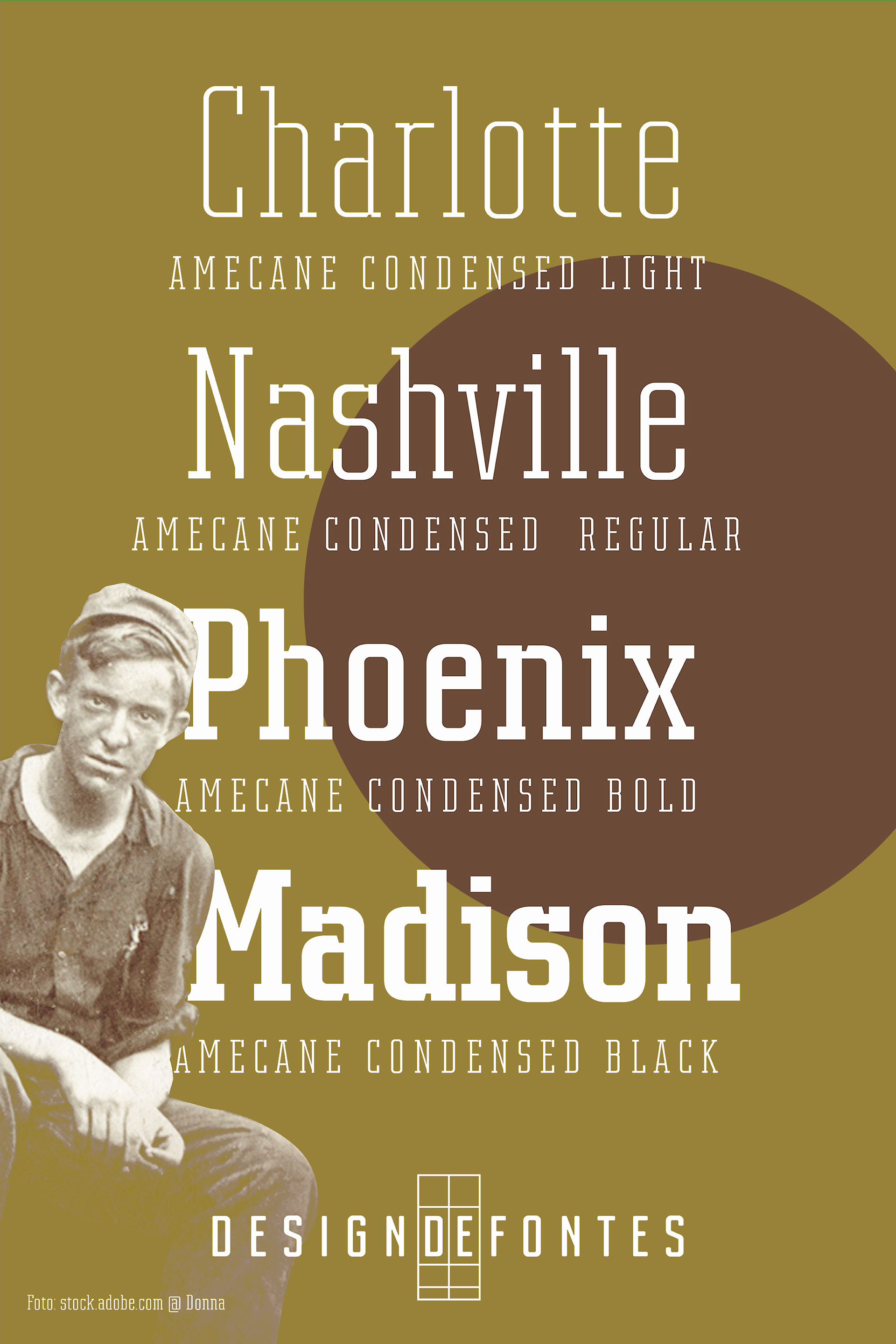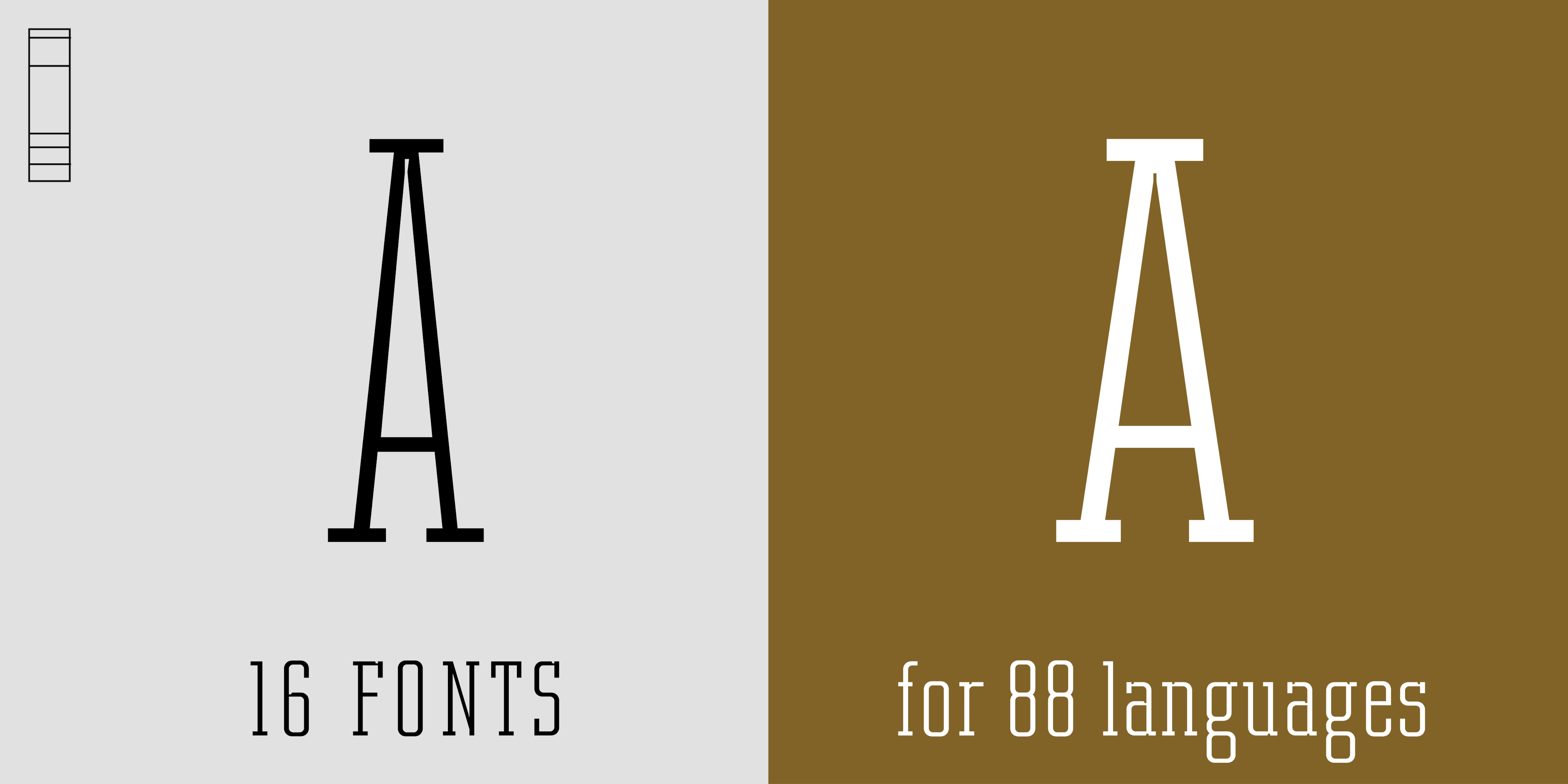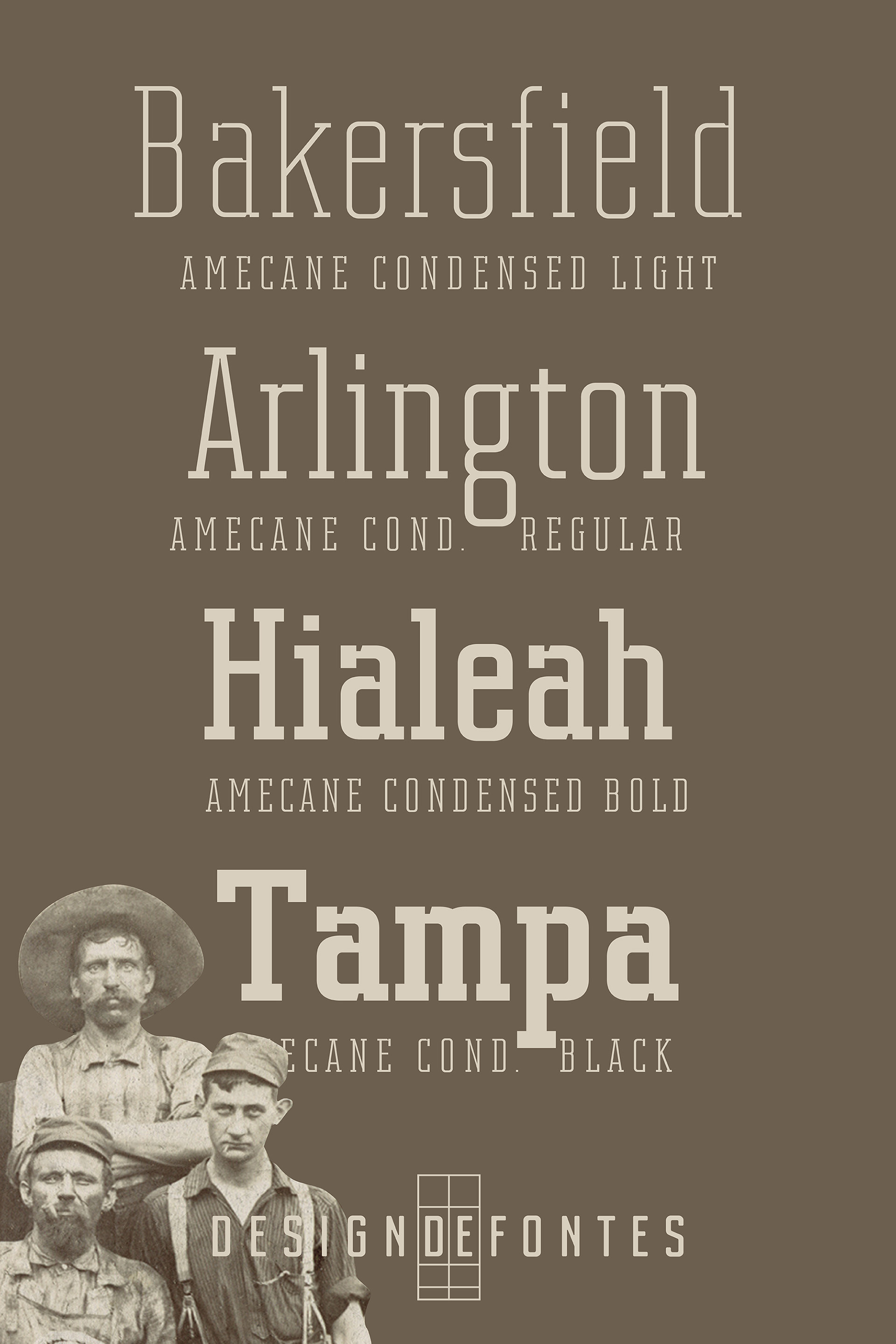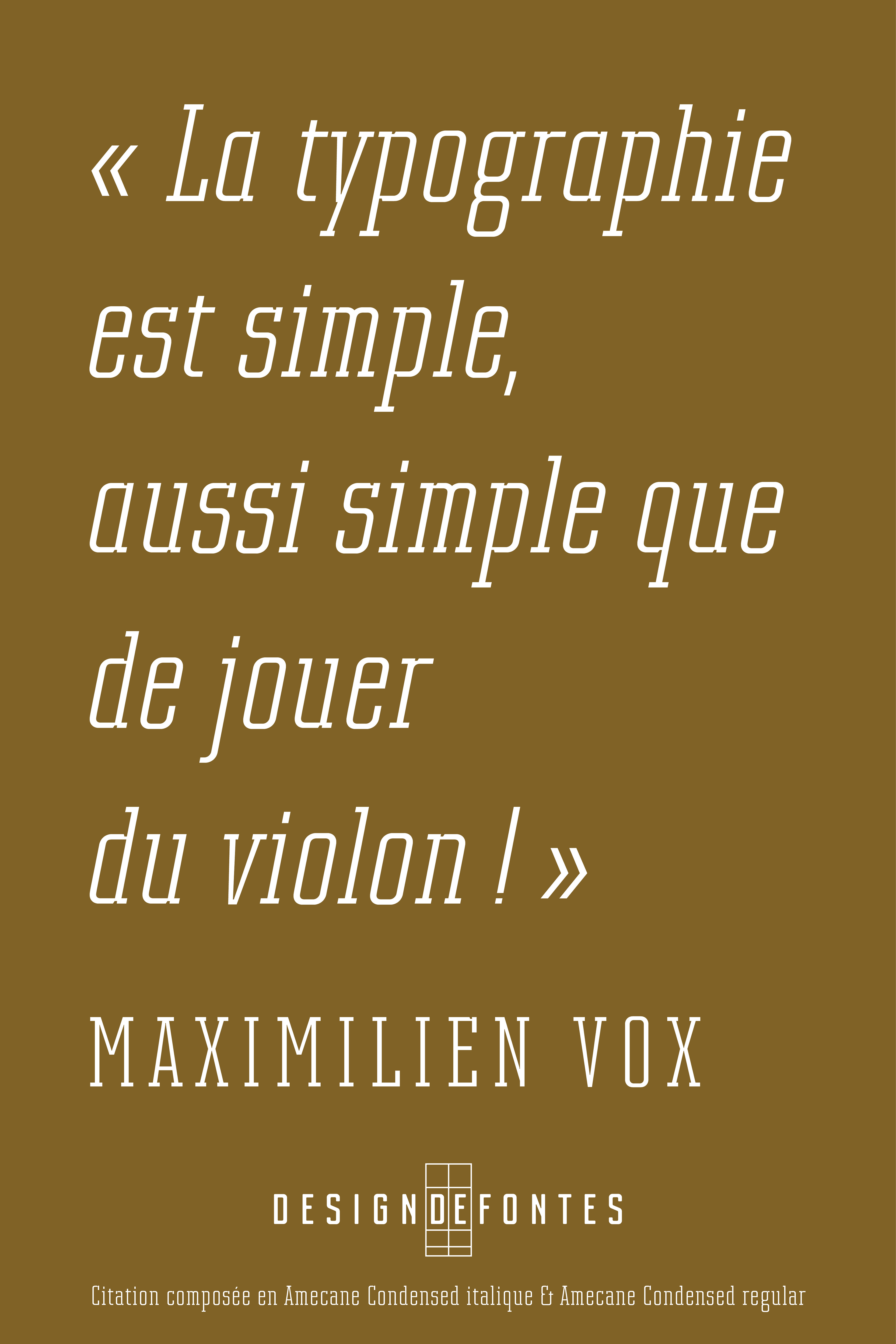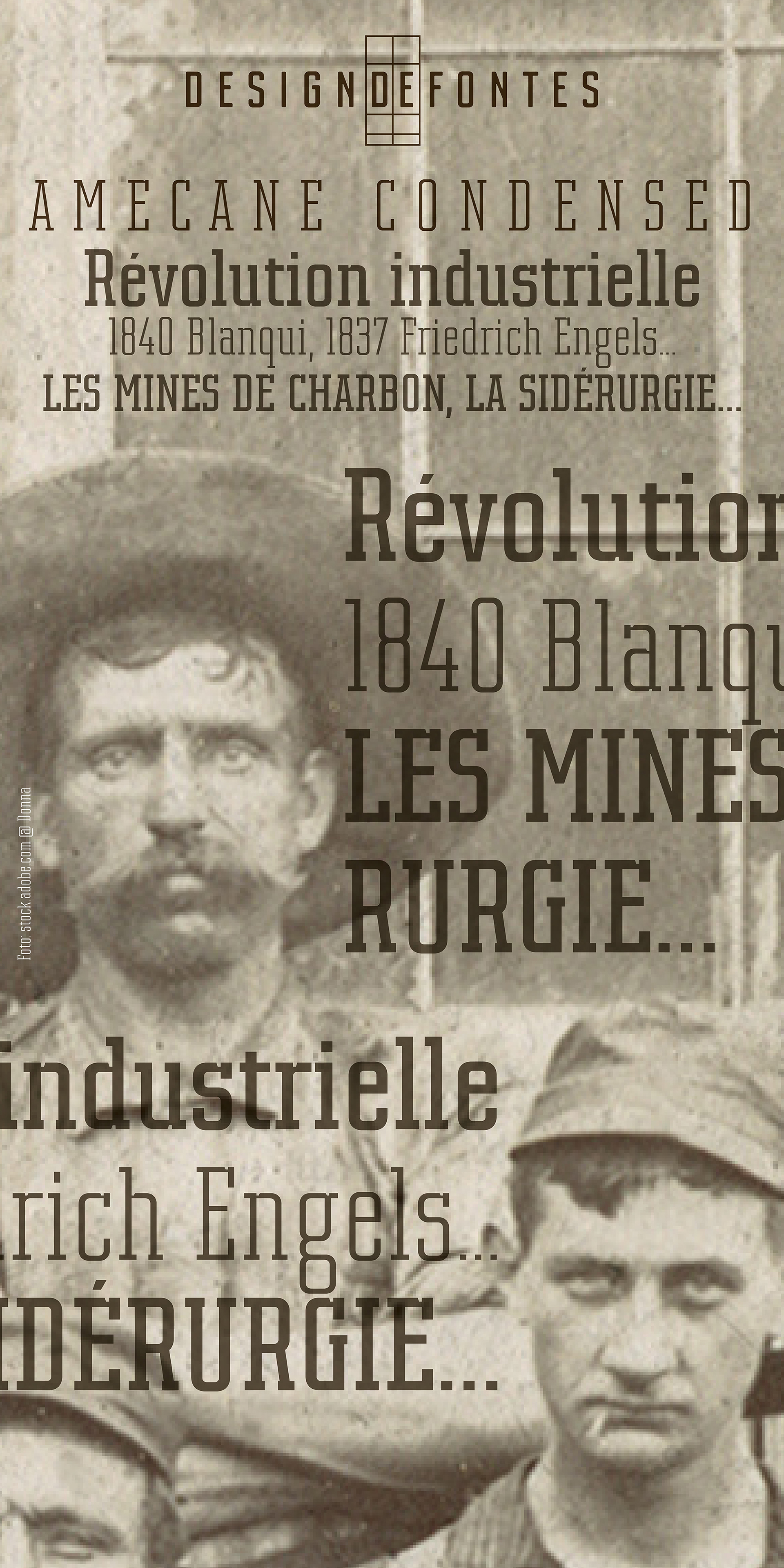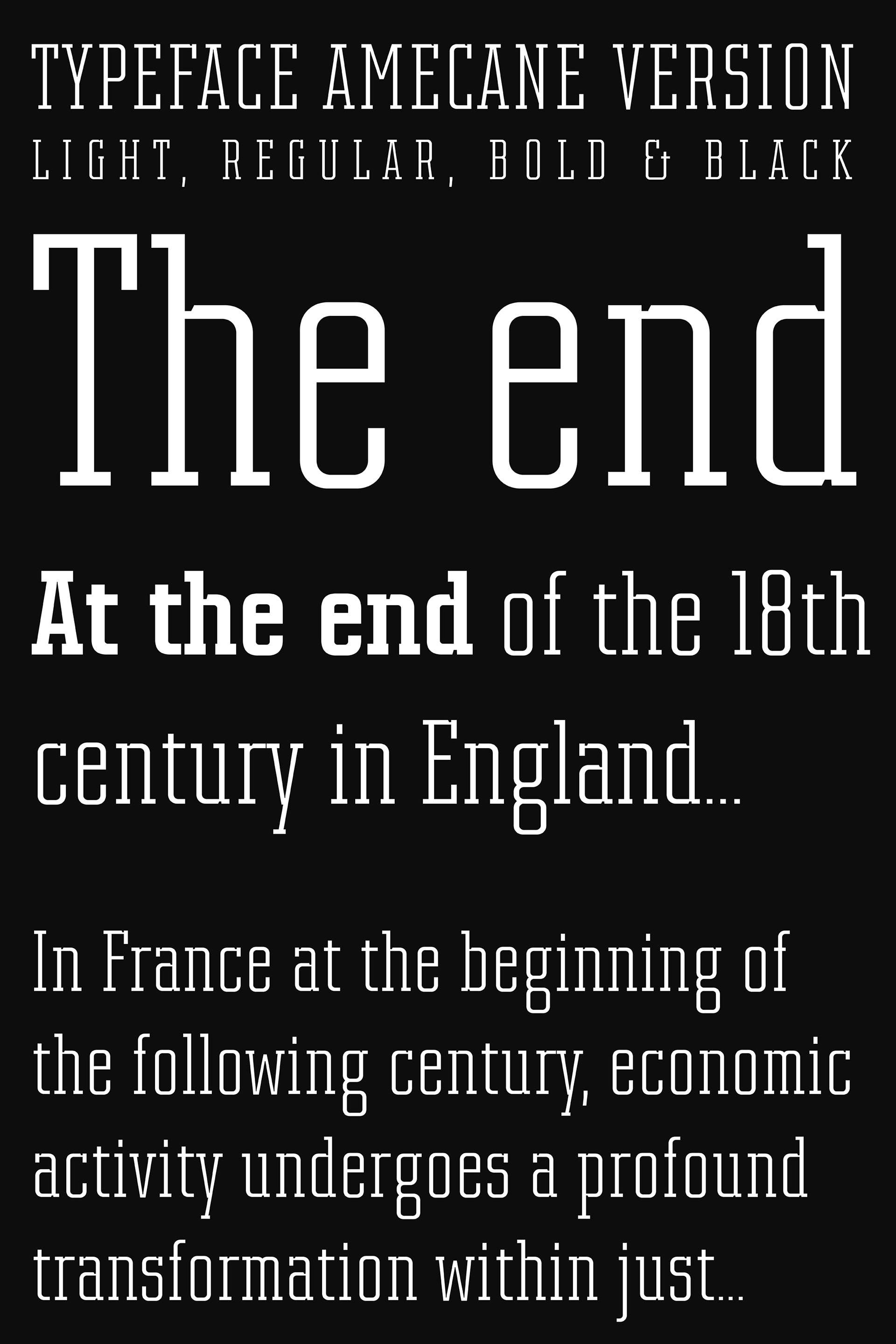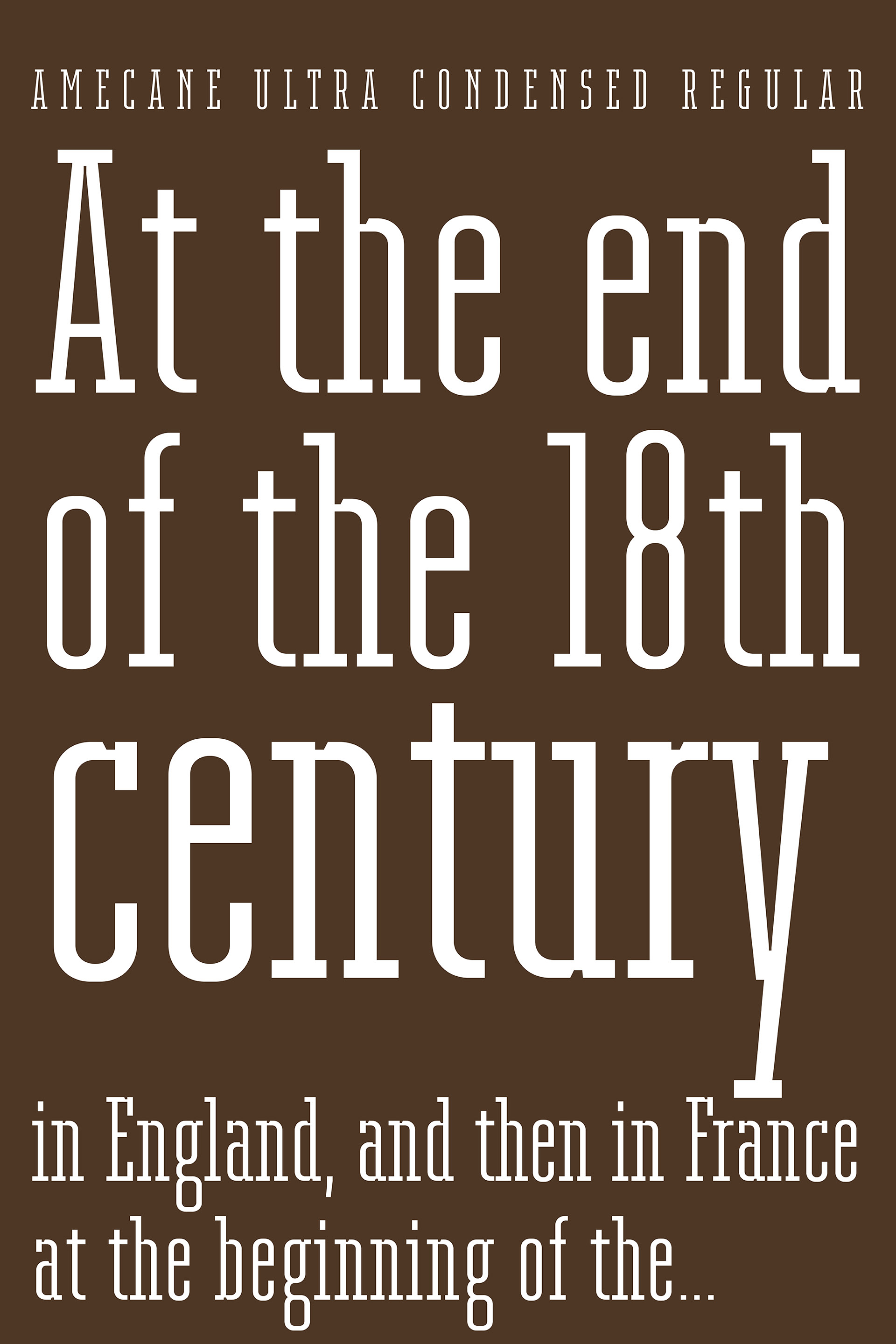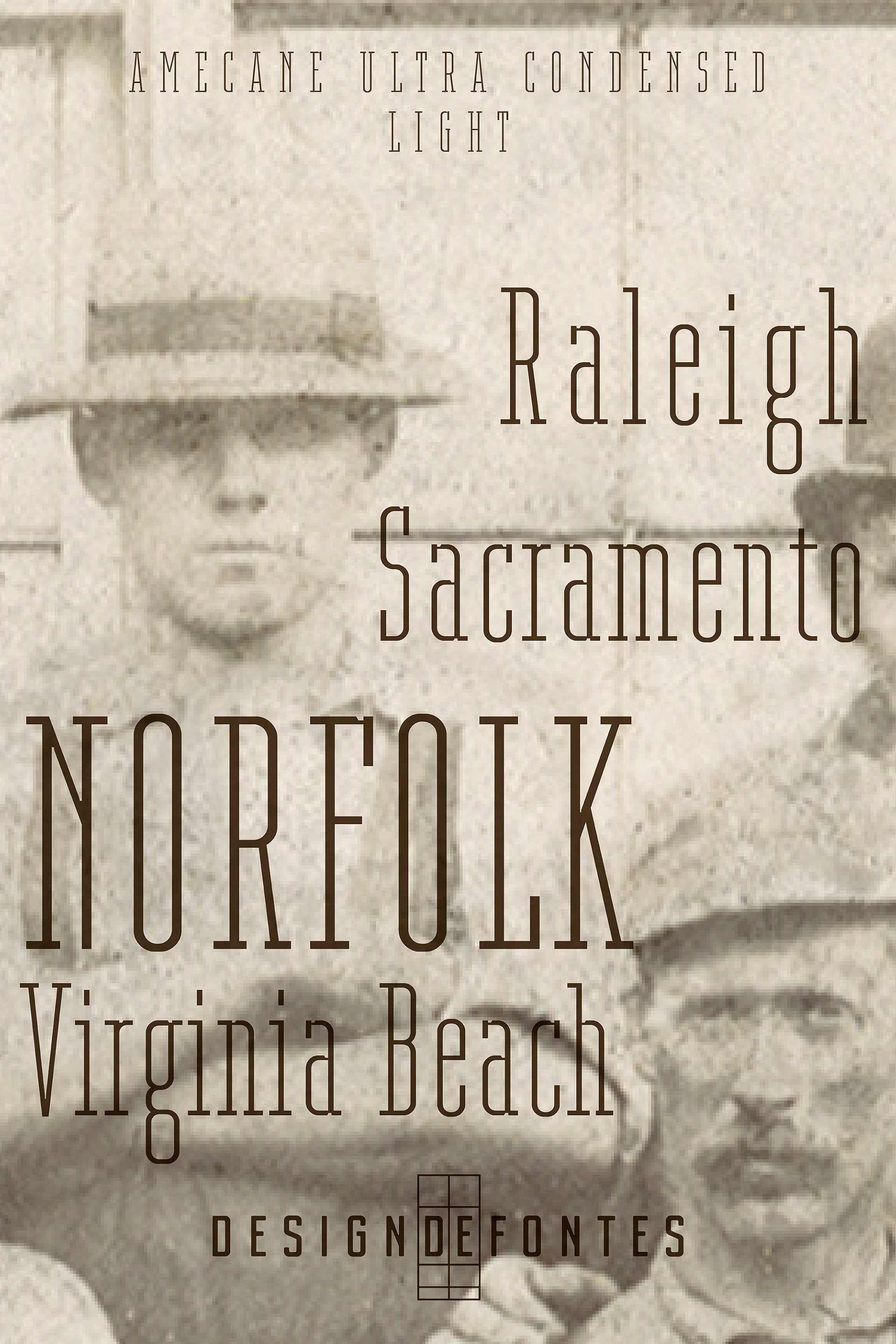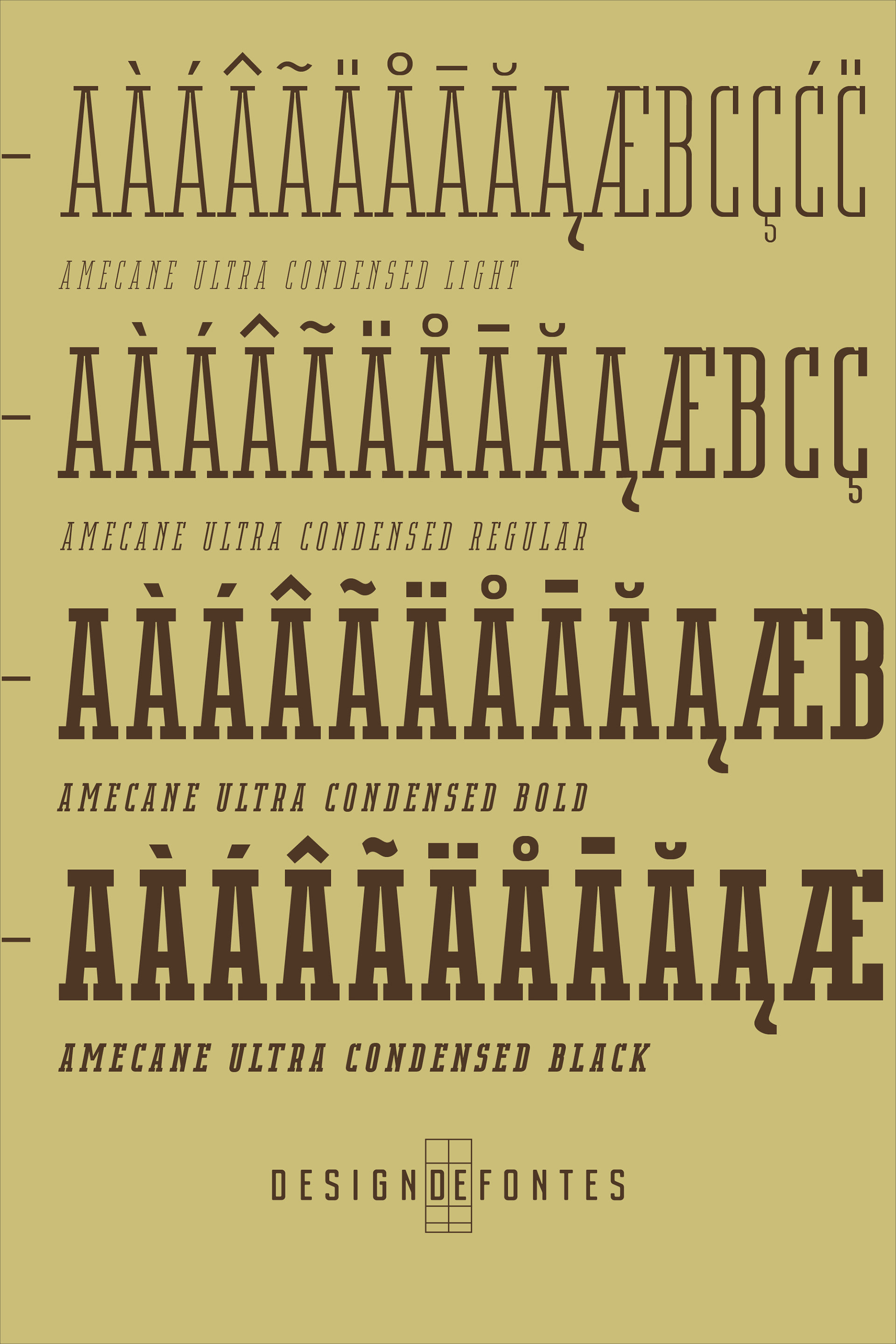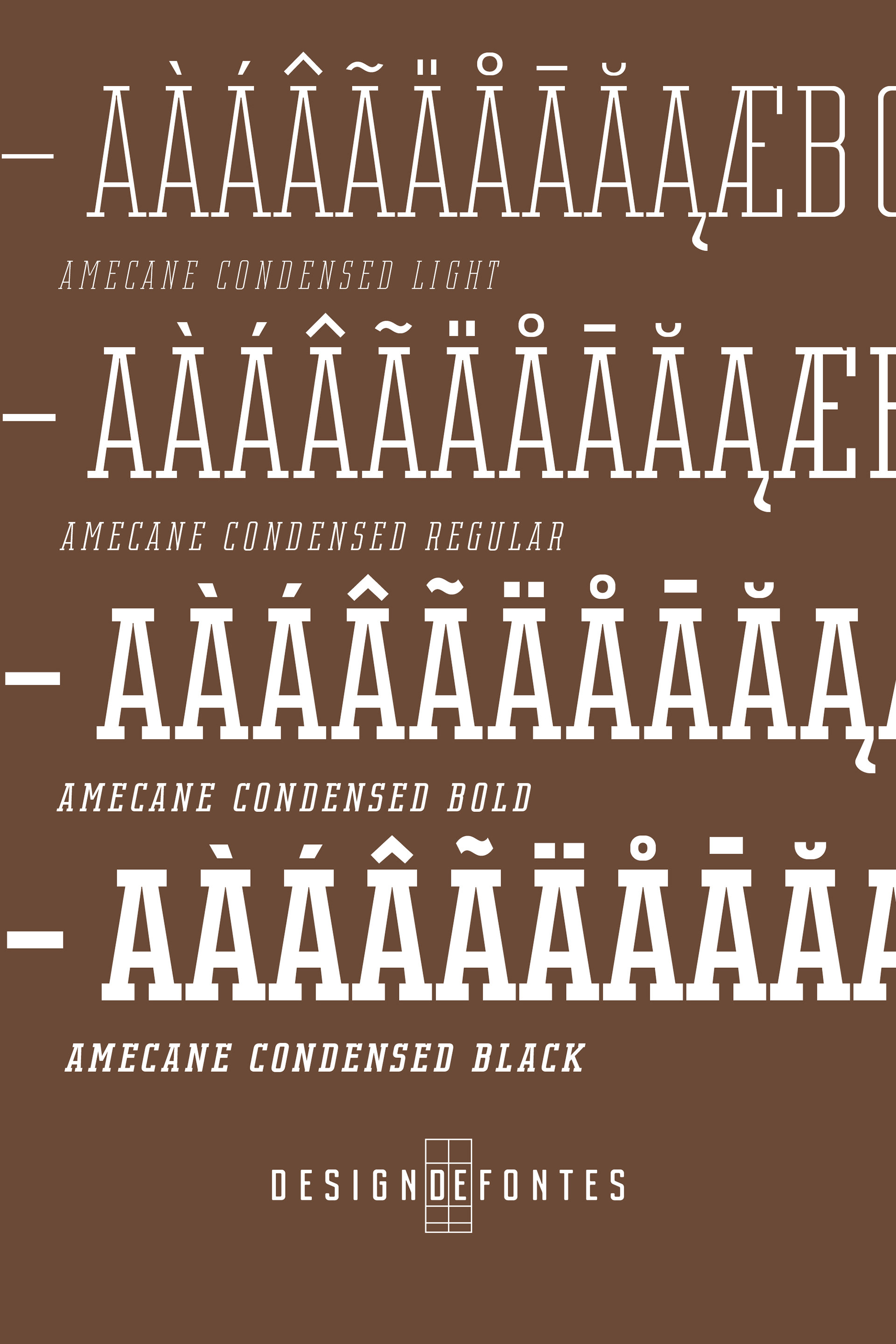
Amecane
Caractère typographique
(Loïc Choquet pour designdefontes, ma fonderie)
Amecane est un caractère inspiré par d’anciens caractères typographiques qui ont été développés au début du XIXe siècle. Ces caractères ont été classés sous le nom d’égyptiennes (Classification Thibaudeau) ou de mécanes (Classification Vox-Atypi). Design : Loïc Choquet.
Le design d’Amecane associe des empattements rectangulaires spécifiques à un design global inscrit dans des formes rectangulaires, associant ainsi un style retro dans des gabarits plus modernes. C’est un caractère qui associe des lignes courbes et des formes anguleuses.
Grâce à ses 348 glyphes Amecane est utilisable pour 88 langues.
Chasses & styles (16 fontes)
Ultra Condensed Light, Ultra Condensed Light Italic, Ultra Condensed, Ultra Condensed Italic, Ultra Condensed Bold, Ultra Condensed Bold Italic, Ultra Condensed Black, and Ultra Condensed Black Italic.
Condensed Light, Condensed Light Italic, Condensed, Condensed Italic, Condensed Bold, Condensed Bold Italic, Condensed Black, and Condensed Black Italic.
Amecane Condensed
Font: Amecane Ultra Condensed Light
Fonts: Amecane Ultra Condensed
AMECANE EST PRÊTE À L’EMPLOI POUR 88 LANGUES DIFFÉRENTES